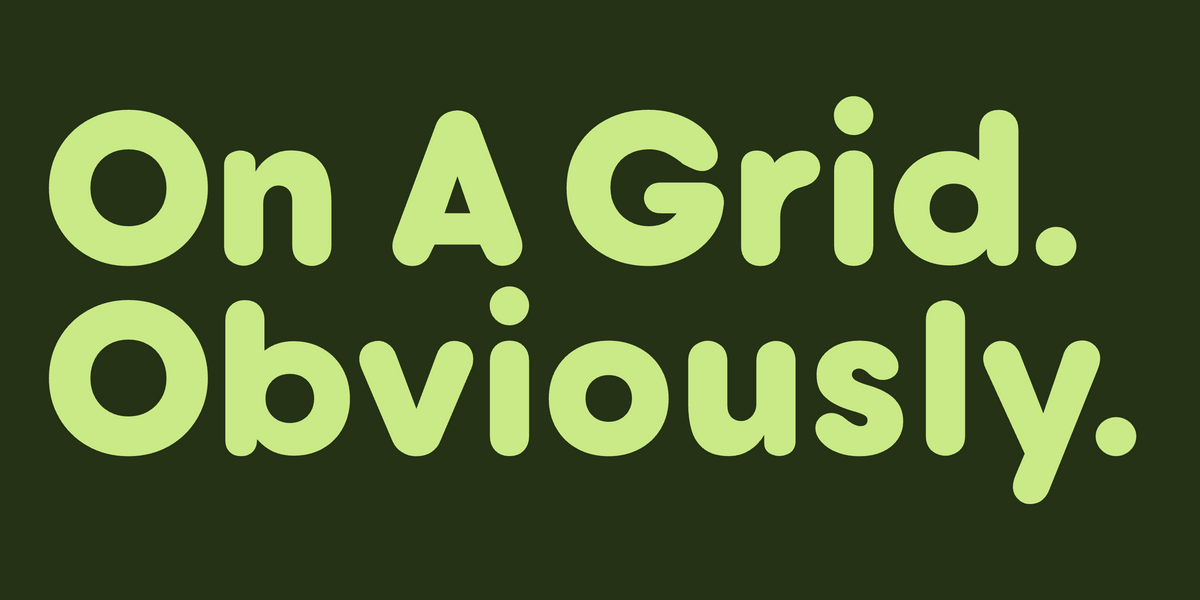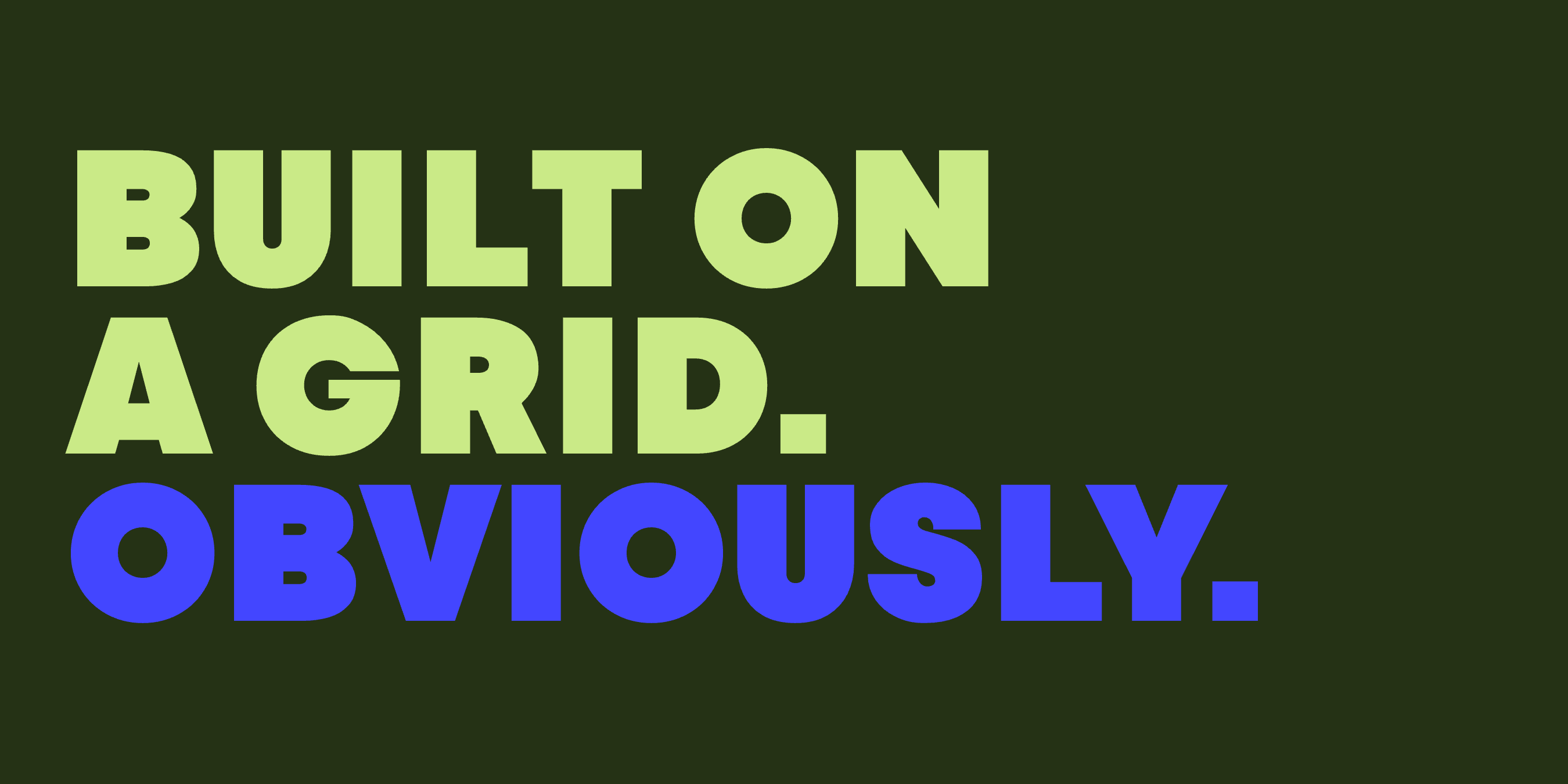
Fuentes sans serif geométricas para un branding moderno
Las fuentes sans serif geométricas se construyen a partir de formas básicas: círculos, triángulos y cuadrados. La o minúscula es un círculo perfecto, la M se abre desde un único vértice y el grosor del trazo se mantiene igual de una letra a otra. No hay serifas, no hay contraste entre trazos gruesos y finos y no hay adornos. Lo que queda es limpio, moderno y visualmente tranquilo.
El género se remonta a 1927 y a Futura de Paul Renner, que definió la sans geométrica del siglo XX. Las sans serif geométricas de hoy siguen la misma lógica, pero añaden detalles sutiles: contraformas redondeadas, terminales más afilados, proporciones más amables. Funcionan bien en branding modernista, diseño editorial, proyectos de tecnología y startups, identidades de museos, moda y cualquier proyecto en el que el diseño deba sentirse estructurado y pensado.
Si buscas en concreto fuentes cuya o minúscula sea un círculo perfecto, consulta nuestro artículo sobre fuentes con la o redonda. A continuación encontrarás nuestras fuentes sans serif geométricas favoritas para probar y comprar, además de algunas Google Fonts gratuitas que encajan.
Cómo reconocer una sans serif geométrica
Cuatro rasgos definen el género:
- O como círculo perfecto: la o minúscula es un círculo de verdad, no un óvalo
- Trazos de grosor uniforme: los trazos verticales y horizontales tienen el mismo grosor (monolineales)
- Sin contraste: el peso se mantiene igual en todos los trazos
- Formas de un solo piso: la a minúscula suele tener un solo ojal, en lugar de los dos de la sans humanista
Las mejores fuentes sans serif geométricas para branding
Apex
Apex es una sans serif geométrica contundente, con puntas afiladas en letras como la A, la M y la W. Los grosores más pesados tienen mucha presencia en titulares y logotipos. La familia completa incluye nueve grosores y una fuente variable.
Probar Apex →Vole
Vole es una sans serif geométrica con contraformas redondeadas y una forma interior fluida. La construcción geométrica se mantiene pura, pero las curvas interiores le dan a Vole un aire tranquilo y acuático en titulares. Nueve grosores y una fuente variable.
Probar Vole →Goji
Goji es una sans serif geométrica redondeada con muchos caracteres alternativos. Tiene un carácter juguetón sobre una estructura modernista limpia, con suficiente flexibilidad estilística para funcionar tanto en branding como en textos más largos.
Probar Goji →Auria Sans
Auria Sans es una sans serif geométrica moderna con esquinas interiores suaves, puntos circulares en la puntuación y glifos alternativos para la r, la A, la M y la W. Su aire ondulado se apoya en una estructura geométrica estricta.
Probar Auria Sans →Ark Sans
Ark Sans parte de una idea arquitectónica. Las diagonales cortadas en la A, la R, la K y otras letras le dan un aire de plano técnico. Pensada para estudios de arquitectura, estudios de diseño e identidades contemporáneas.
Probar Ark Sans →Bitec
Bitec es una sans serif geométrica limpia y contemporánea, pensada para tecnología, startups y diseño editorial. Es la fuente de texto de la tienda fonts.mojomox.com.
Probar Bitec Sans →Scal
Scal es una sans geométrica moderna inspirada en Futura, con terminales más afilados y curvas más redondas que el original. ADN geométrico con un toque contemporáneo para logotipos y titulares.
Probar Scal →Bool
Bool es una sans serif geométrica juguetona con detalles en punta en la A, la M, la N y la W. La base geométrica mantiene la fuente limpia y modular, mientras que las puntas le dan energía visual.
Probar Bool →Mosy
Mosy es una sans serif geométrica amable, con proporciones más suaves que una geométrica Bauhaus estricta. Va bien con marcas que quieren claridad modernista con un carácter más cálido.
Probar Mosy →Nano
Nano es una sans serif geométrica contundente con detalles de carácter matemático. Pensada para branding de ciencia, tecnología, ingeniería y editorial contemporáneo, donde la propia fuente debe transmitir precisión.
Probar Nano →Fuentes sans serif geométricas gratuitas (Google Fonts)
11. Poppins
Poppins es una sans serif geométrica con una o perfectamente circular, trazos uniformes y una amplia gama de grosores. Muy conocida y con buen soporte, es una opción gratuita fiable para trabajos modernistas cuando una licencia comercial no entra en el presupuesto.
12. Montserrat
Montserrat tiene inspiración geométrica y un carácter propio muy marcado. Varios grosores, buen soporte en todos los navegadores y una fuente de confianza muy conocida para proyectos de tecnología y startups.
Cómo elegir
Para branding de startups y tecnología, Bitec, Nano o Scal. Para branding de producto con un tono amable, Goji o Mosy. Para estudios de arquitectura y diseño, Ark Sans o Scal. Para titulares juguetones, Bool, Apex o Plox. Para textos largos y sistemas de marca en los que la fuente debe pasar desapercibida, Vole, Auria Sans, Bitec o Goji.
Para otro artículo sobre una letra en particular, consulta Apex, fuente con A triangular: Apex tiene cuatro diseños alternativos de la A mayúscula (en punta, con travesaño triangular, triángulo en contorno y triángulo relleno).